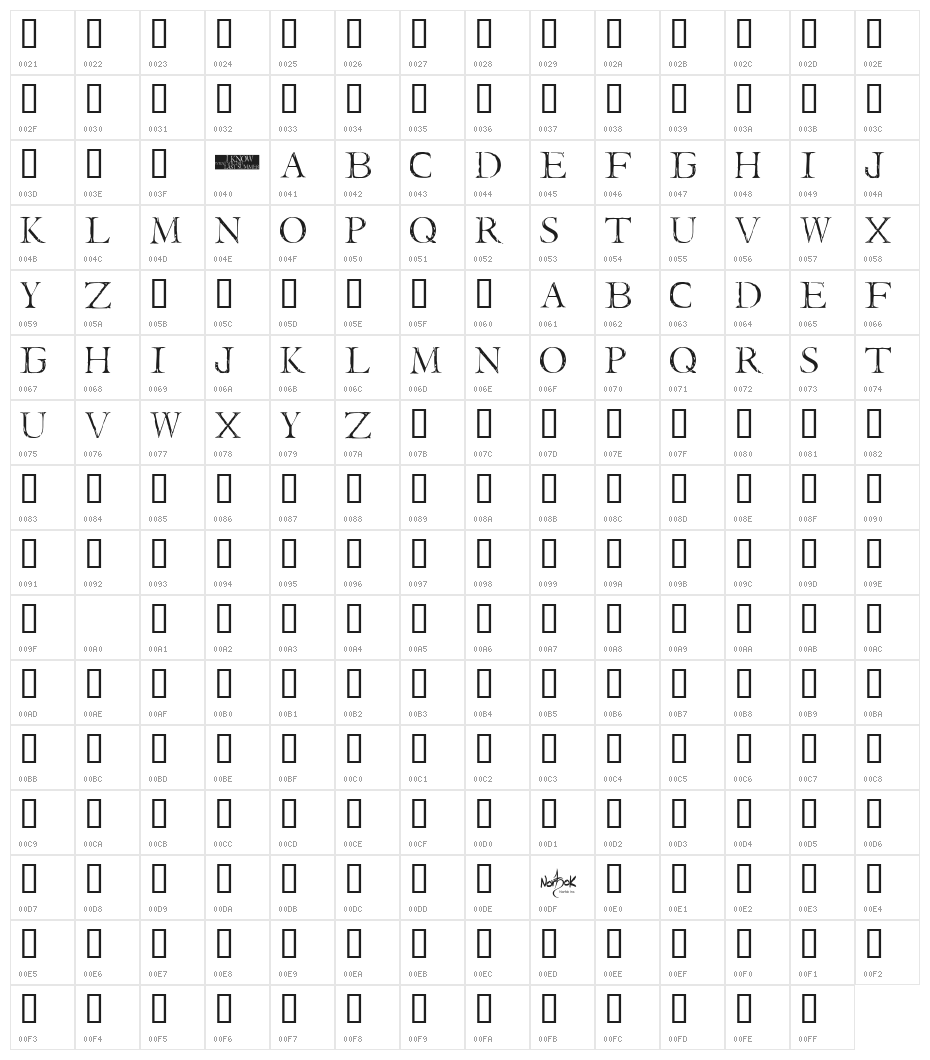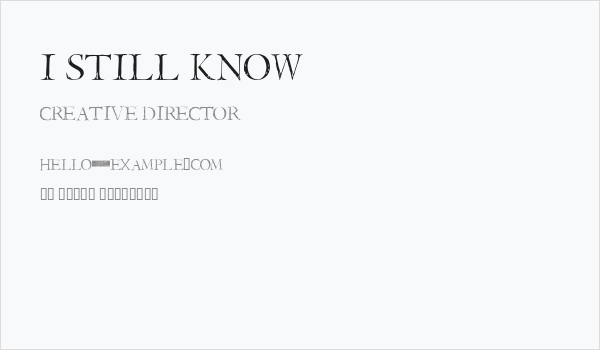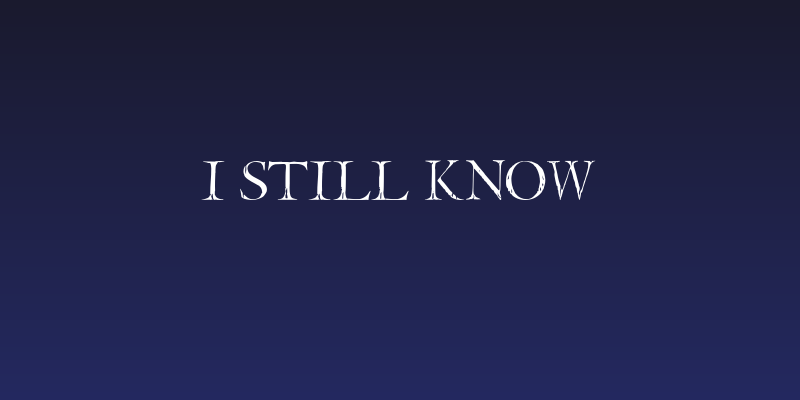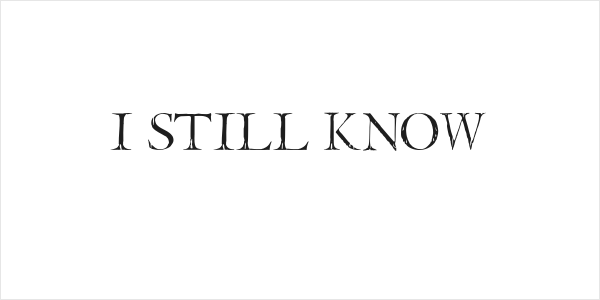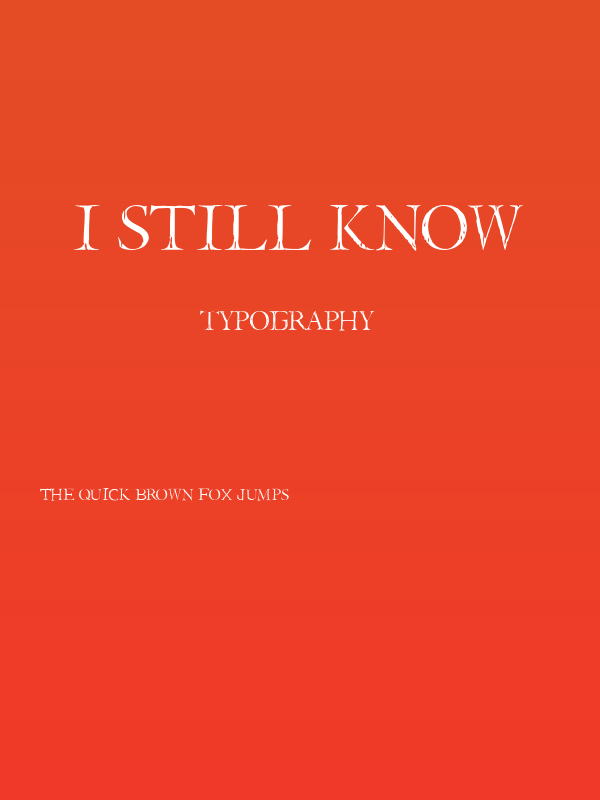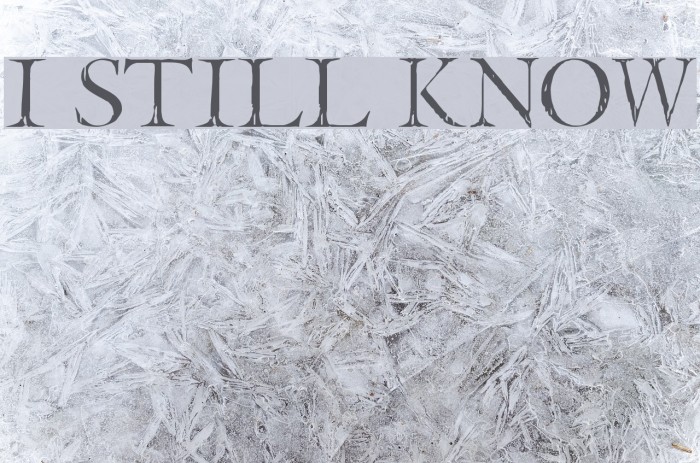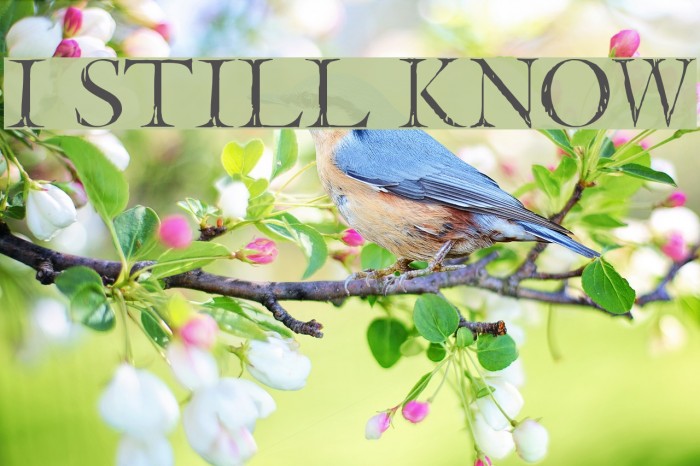
I Still Know Font
| Категория | Horror |
| Общий стиль | Vintage |
| Рекомендуемые проекты | Ideal for vintage posters, album covers, branding for rustic or industrial-themed businesses, and any design project seeking a rugged, historical aesthetic. |